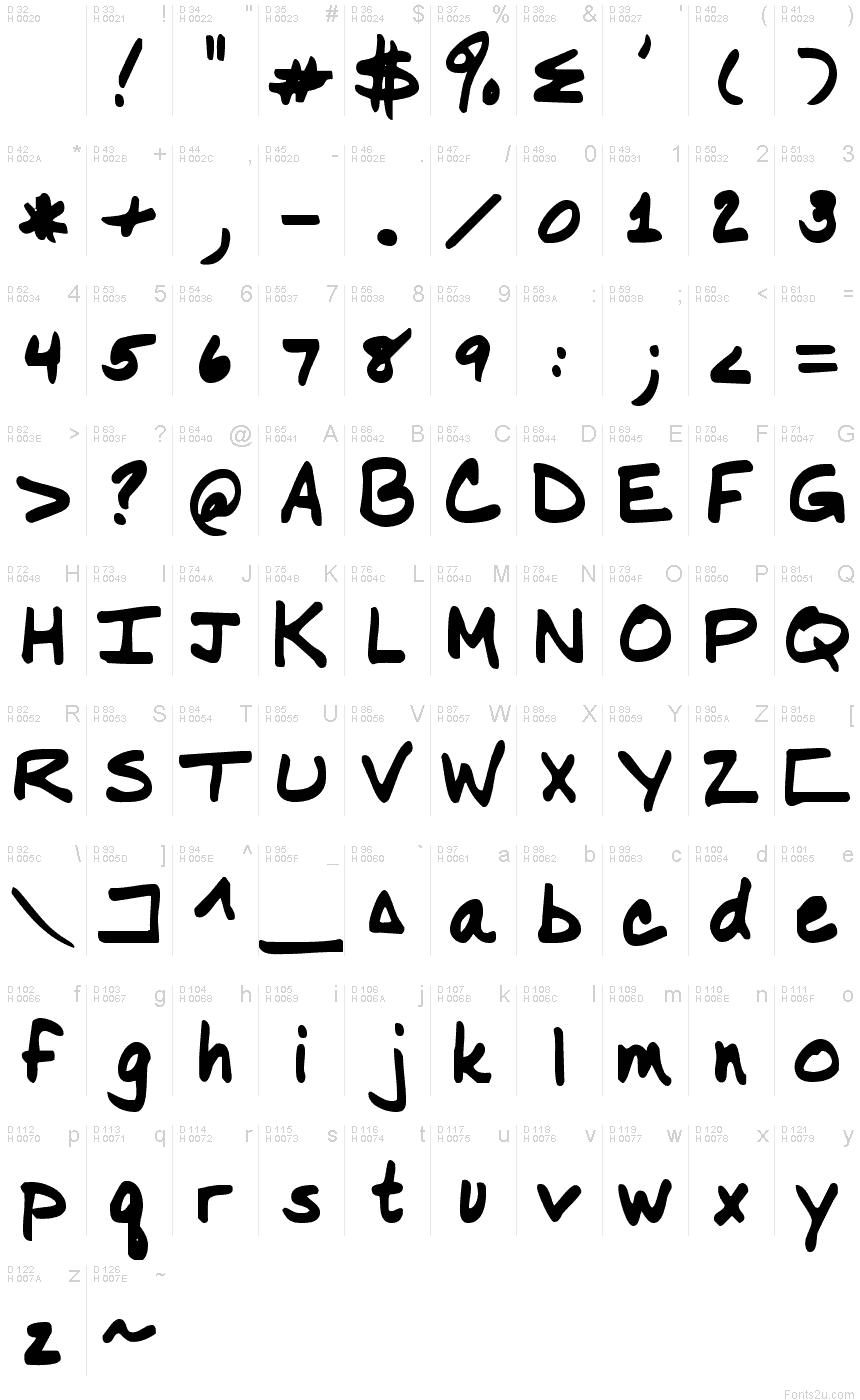
Nancy, bezplatné ručně psané písmo od autorky Ellinor, má široké, zaoblené tahy jako od rychlého fixu, nikoliv úhledné tahy perem. Díky nepravidelnému rytmu a mírně nadýchaným křivkám působí ležérně a osobně, jako by byl text na přání nebo cedulku nahozen jedním sebejistým tahem.
Tato uvolněná ruční textura skvěle zapadne na přáníčka, nadpisy ve scrapbookech, dárkové visačky, cedule do kaváren nebo neformální obaly, kde by uhlazené písmo působilo příliš upjatě. Nancy také skvěle ukotví grafiku na sociální sítě nebo pozvánky, zejména když krátká slova potřebují hřejivý, známý tón namísto přísného geometrického řádu.